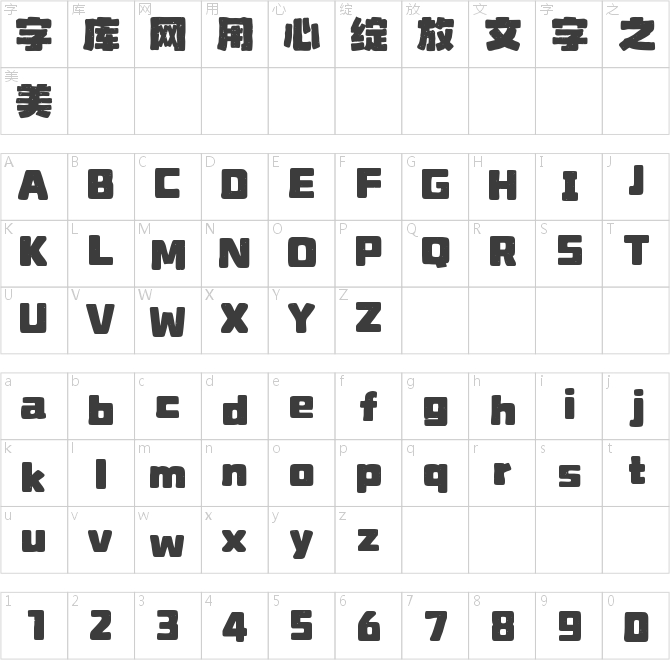
字体名称: 山海黄油曲奇W
山海黄油曲奇W
山海黄油曲奇W介绍
山海黄油曲奇,是一款卡通风字体,包含简繁汉字9169个。该字体是一款具有强劲视觉冲击力的粗体字体。字形粗大,充实填满整个字框。风格童趣,结构多变灵动,线条柔和。字形中融入手绘风元素及手绘镂空元素,宛如一个个黄油曲奇饼干,造型生动有趣,具有灵活的适用性,天真俏皮又不失时尚感。